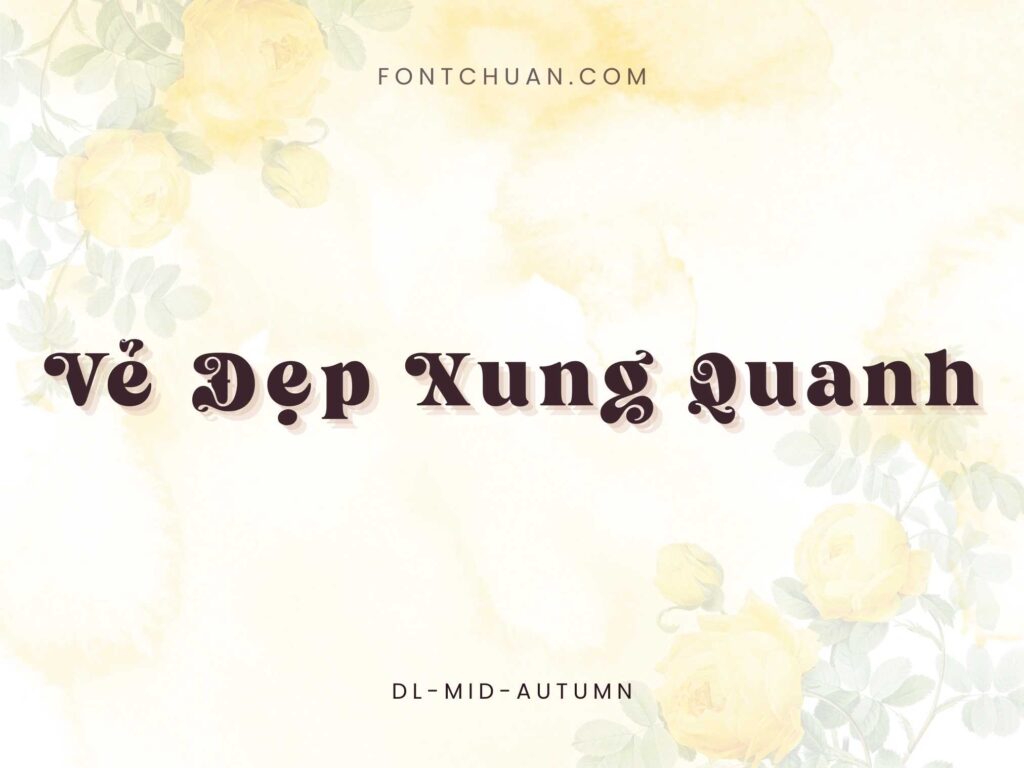
Font DL Mid Autumn Việt Hóa
Mid Autumn là một font chữ mang đậm nét truyền thống Á Đông, được thiết kế để tôn vinh vẻ đẹp và ý nghĩa của Tết Trung Thu. Với các đường nét mềm mại và tinh tế, font này gợi nhớ đến những hình ảnh quen thuộc trong văn hóa Trung Thu như đèn lồng, mặt trăng và hoa văn cổ điển. Nhờ sự Việt hóa của Tduy, Mid Autumn hỗ trợ đầy đủ tiếng Việt, giúp người dùng dễ dàng ứng dụng trong các thiết kế mang đậm bản sắc dân tộc. Thành viên của Font Chuẩn đã sưu tầm và chia sẻ font này nhằm đáp ứng nhu cầu của cộng đồng thiết kế.
Về đặc điểm thiết kế, Mid Autumn sở hữu các ký tự được chạm khắc tỉ mỉ, kết hợp giữa yếu tố truyền thống và hiện đại. Font này bao gồm đầy đủ chữ hoa, chữ thường, số và các ký tự đặc biệt, mang lại sự linh hoạt cho các nhà thiết kế trong việc sáng tạo. Mid Autumn đặc biệt phù hợp cho các dự án như thiết kế thiệp mời, poster sự kiện, bao bì sản phẩm và các ấn phẩm quảng cáo liên quan đến Tết Trung Thu. Ngoài ra, font này cũng thích hợp cho các sự kiện lễ hội khác, mang lại không khí ấm cúng và gần gũi. Trong lĩnh vực ngành nghề, Mid Autumn được ứng dụng rộng rãi trong quảng cáo, thiết kế đồ họa, ẩm thực và văn hóa, góp phần tôn vinh và bảo tồn những giá trị truyền thống.